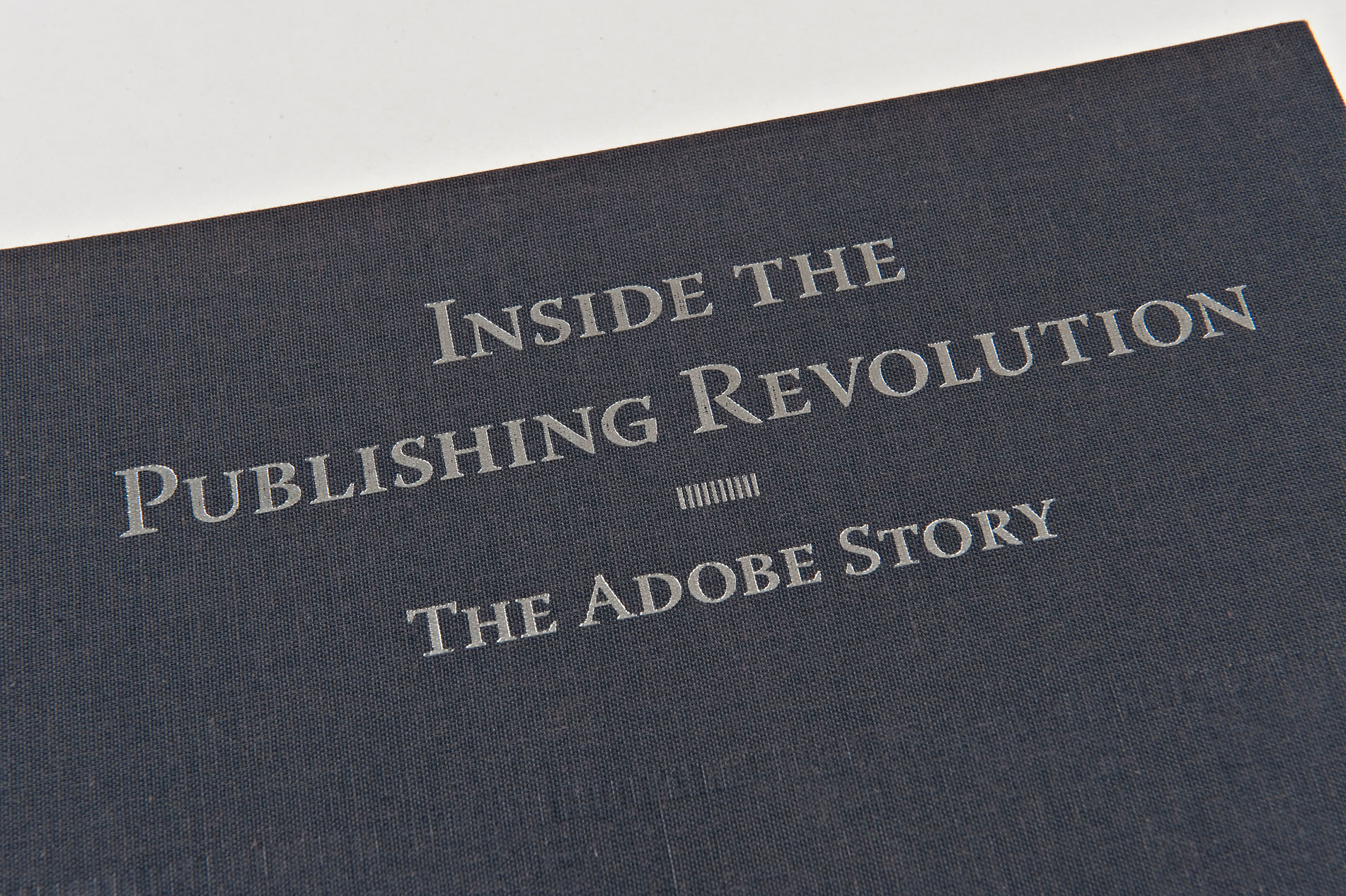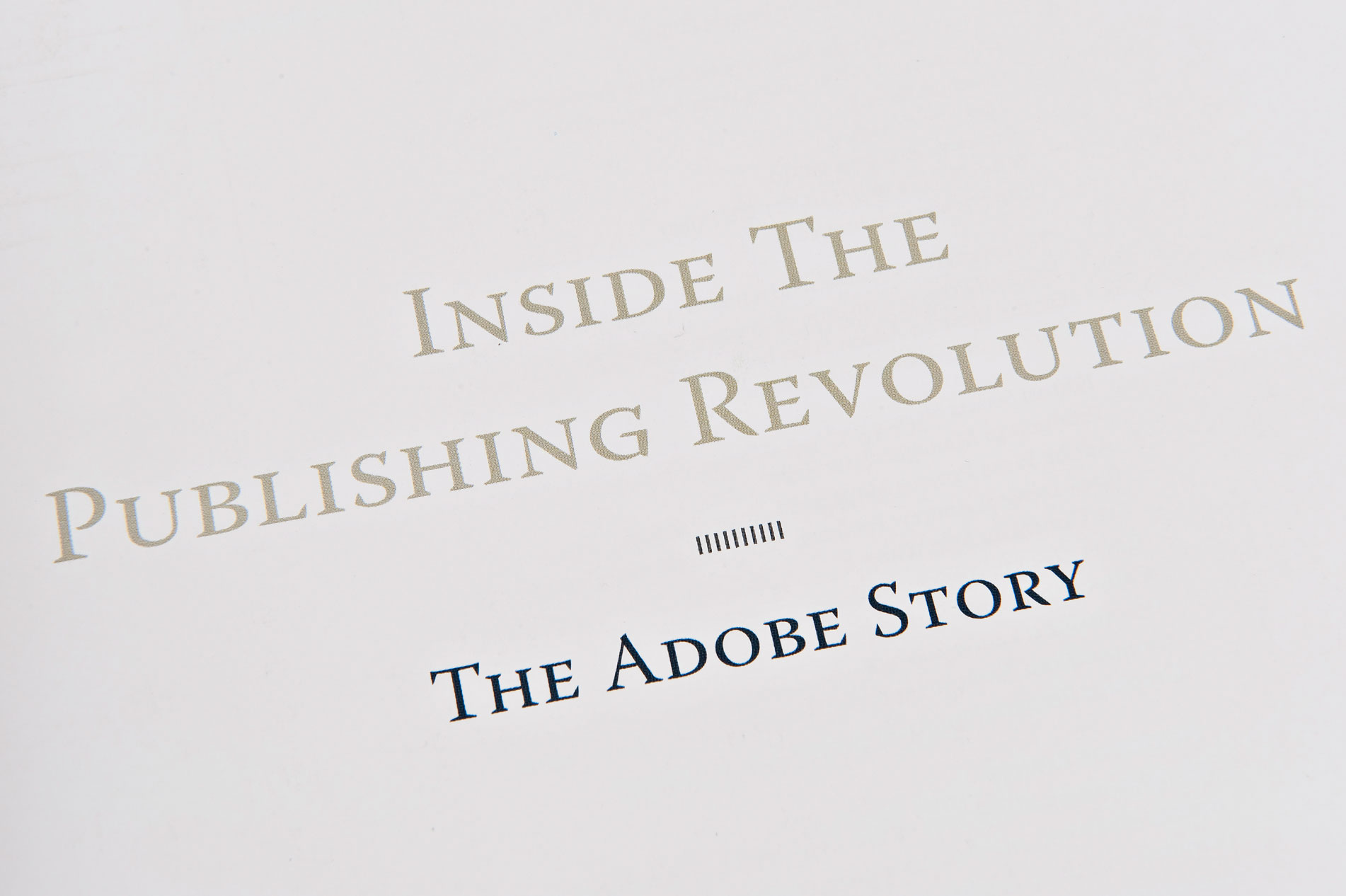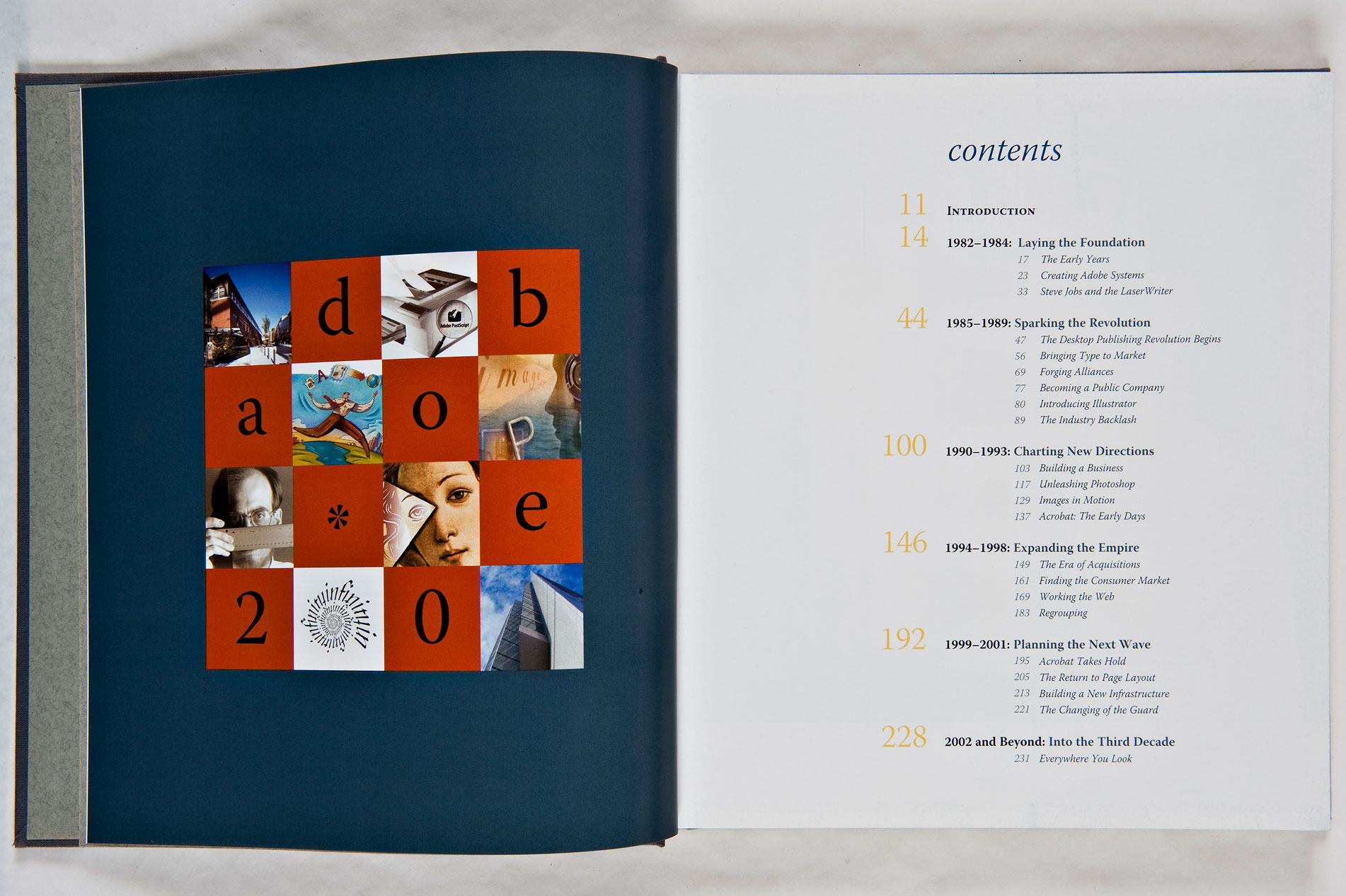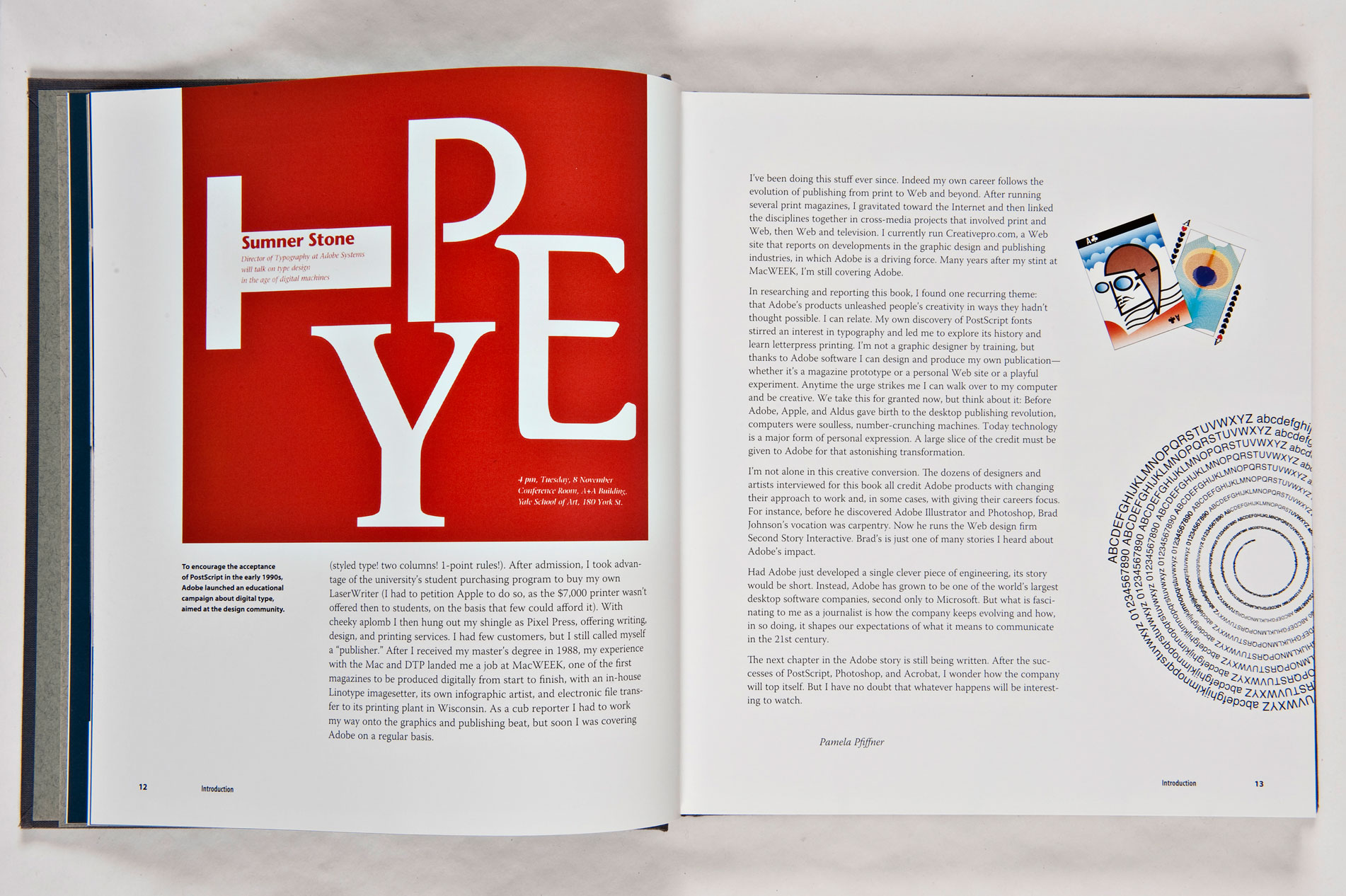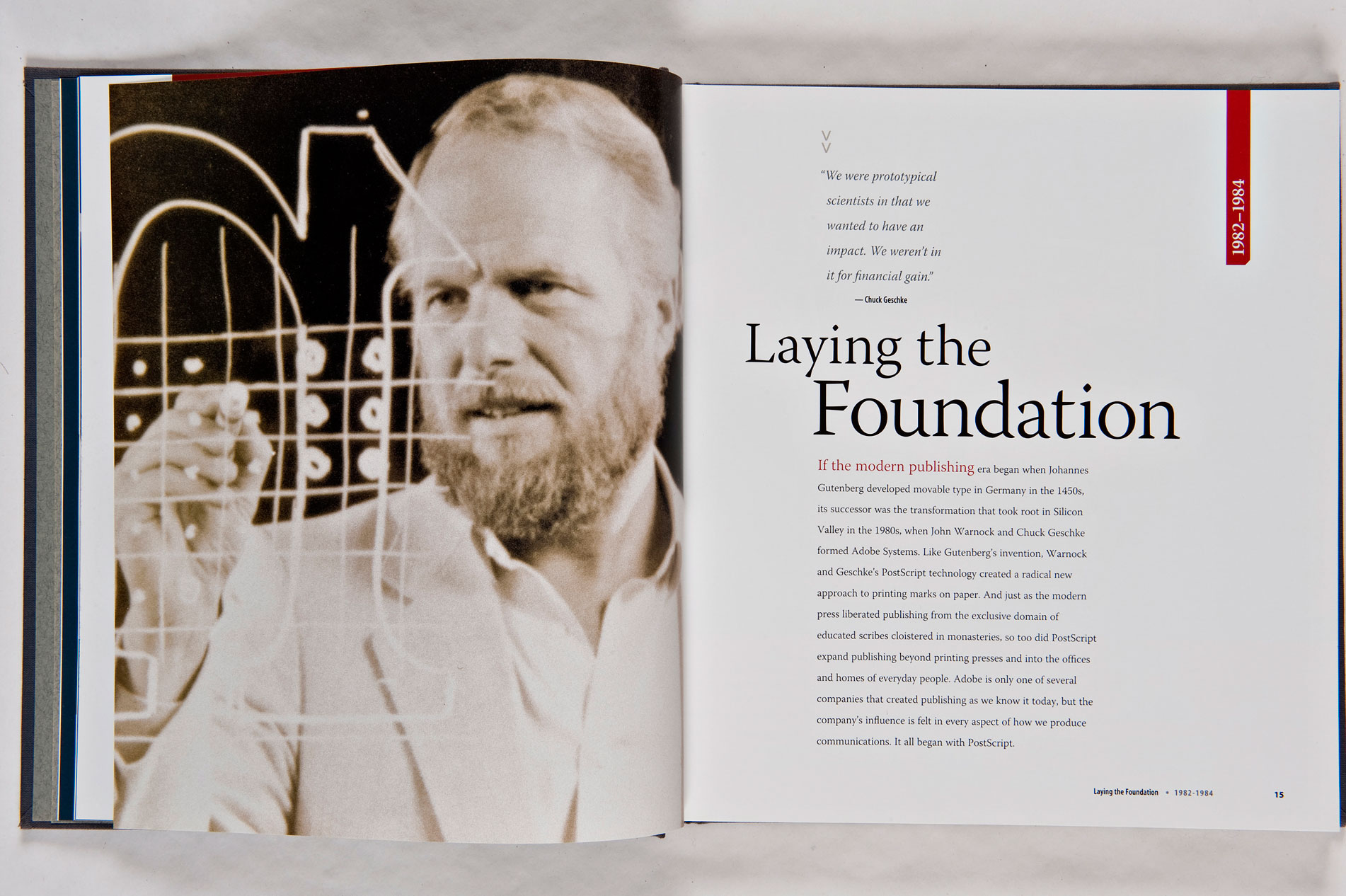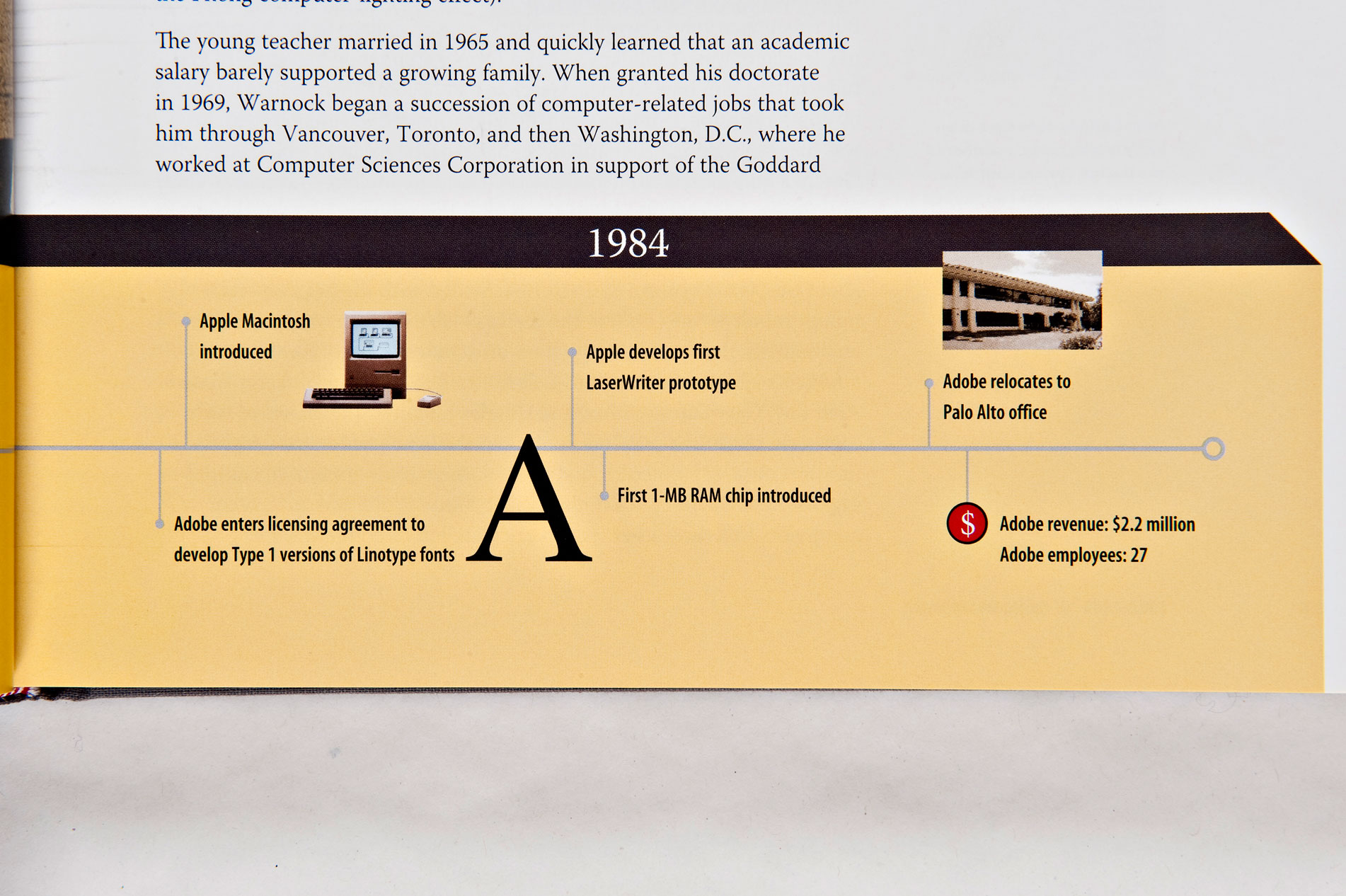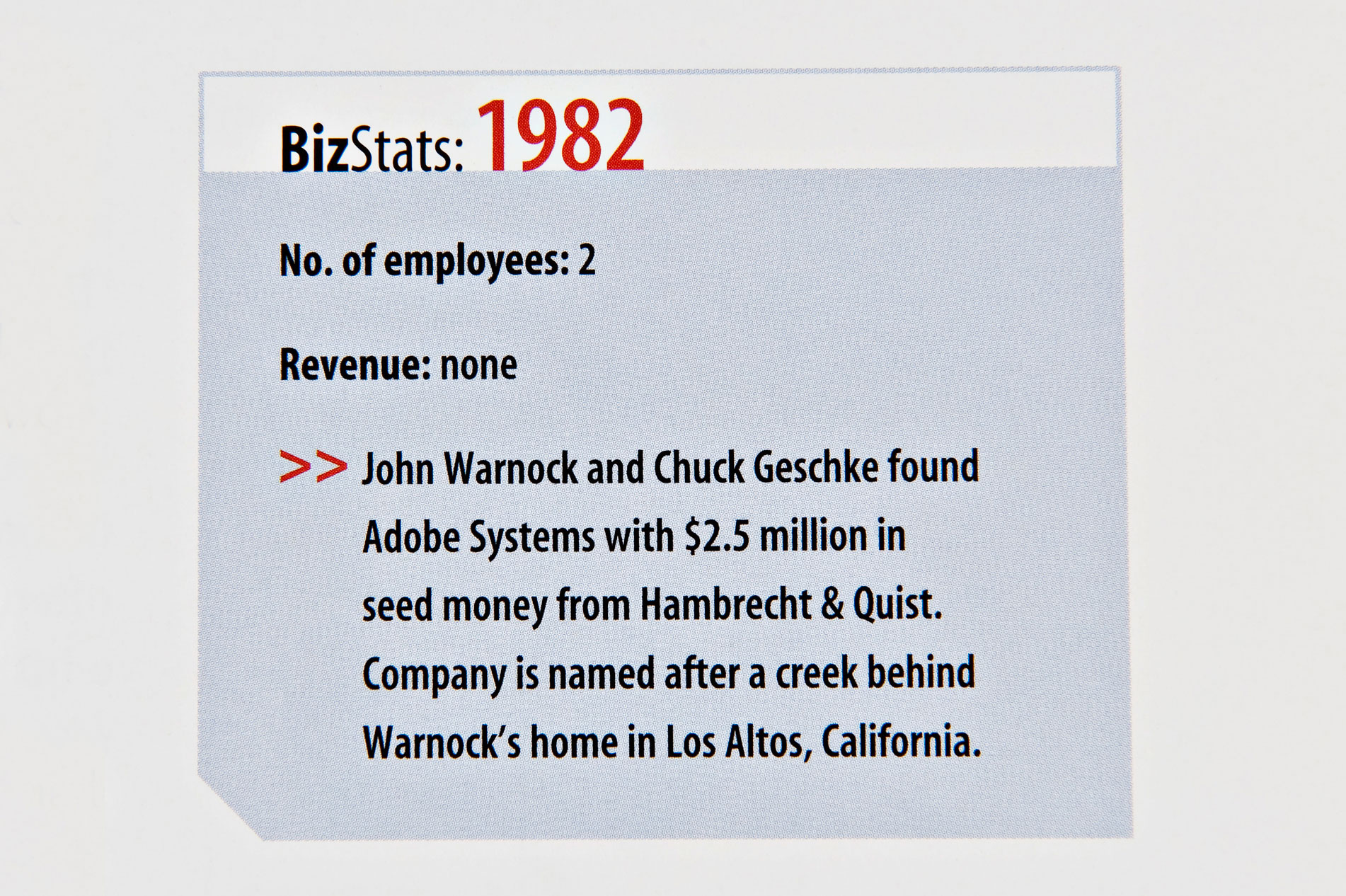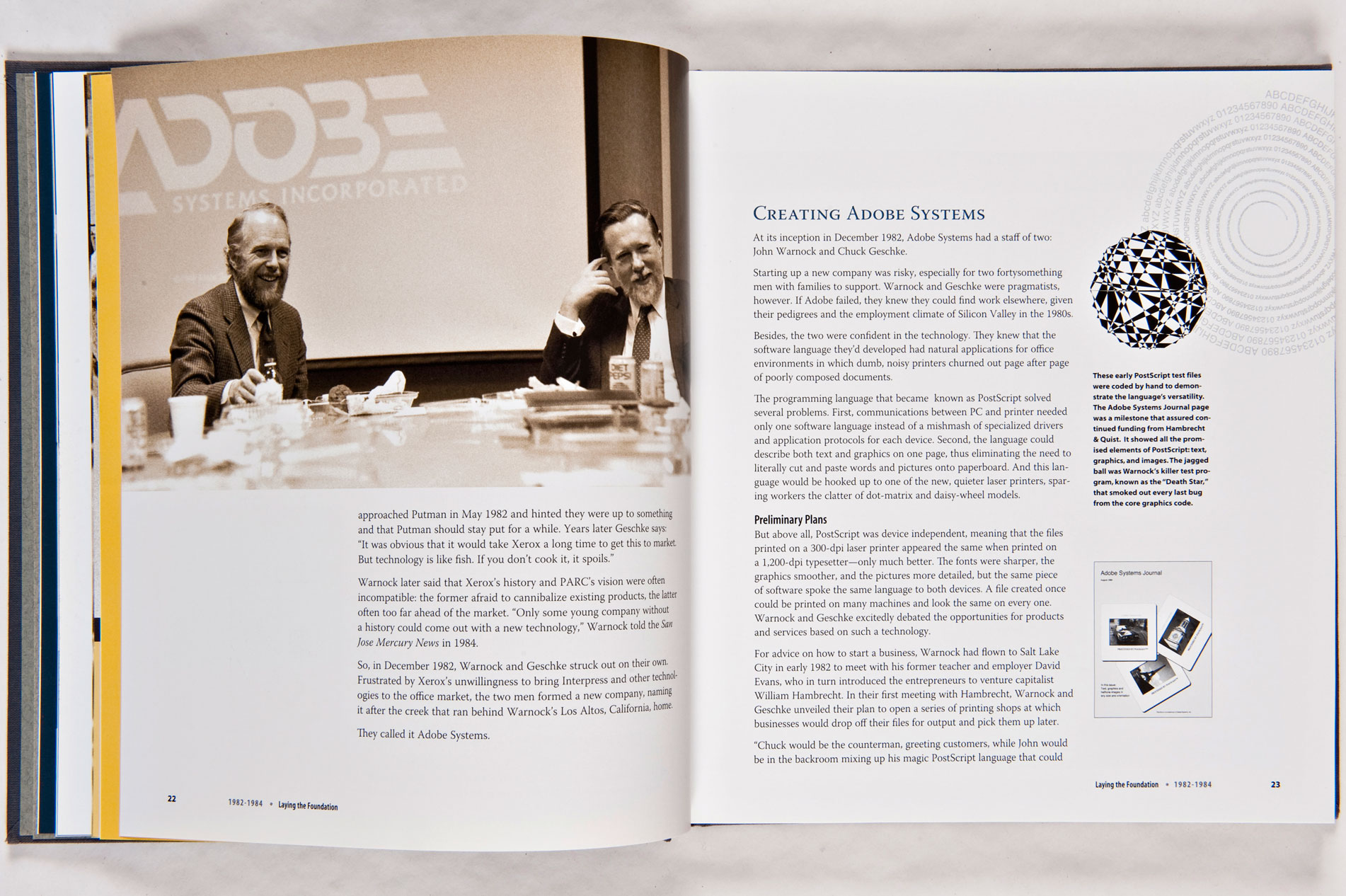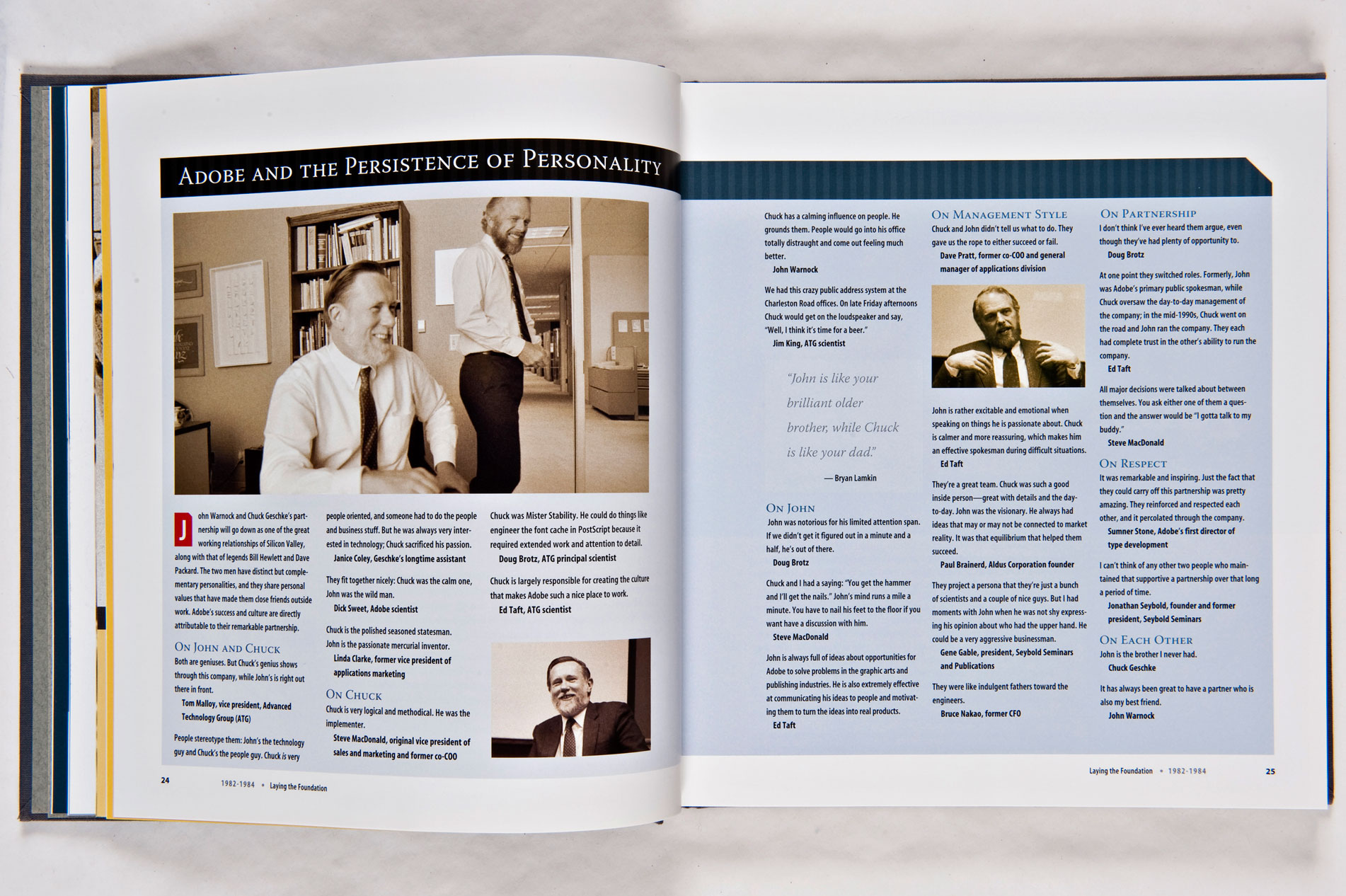
2001-2002 voit la naissance d’e-artsup, l’école supérieure de la création numérique. C’est très exactement 20 ans après la naissance de la société Adobe et des technologies qui allaient bouleverser le monde moderne. C’est pour mieux comprendre ces mutations, et les raisons qui ont fondé la création de notre école, que j’ai publié ce billet.
Ceci est la vidéo d’un simple livre. Mais, but what a book! celui qui reconsidère toute l’histoire vécue de l’aventure de la naissance du monde numérique tel qu’on le connait aujourd’hui. Le monde de digital est passé en vectoriel, les courbes de Bézier ont servi de tremplin pour le langage Postscript inventé par l’équipe de John Warnock. Puis ils connectent une Laserwriter postscript à un Macintosh (Steve Jobs 1985), puis, ils inventent les polices de Type I tout en faisant cadeau à l’humanité des brevets sur le Postscript (1989). Puis ils lancent dans la foulée Adobe Type Manager (ATM) qui permet enfin un vrai WYSIWYG à l’écran etc. 20 ans d’innovations qui ont bouleversé le monde à jamais. Et donc 1989-2009 nous fêtons cette année le vingtième anniversaire de cette naissance Grand Public, avec l’arrivée d’ATM.
Ne reste plus qu’à vous poser une question: si vous aviez l’âge de vivre ces mutations majeures et que vous travailliez à l’époque dans une agence de communication ou dans un bureau de créa, ou encore dans un studio de graphiste, comment avez-vous perçu ces évolutions? comment les avez-vous vécues dans votre quotidien?
Ce magnifique ouvrage à la gloire de l’histoire du langage Postscript et des innovations qu’Adobe a initié depuis plus de 20 ans est encore disponible sur le site d’Amazone, il s’agit pour le coup sans doute d’une édition quasi épuisé et j’espère qu’un jour il sera réédité tant il contribue à mieux nous faire comprendre les processus scientifiques, techniques, marketing et sociales qui ont changé notre monde d’avant en un monde de création à la portée du grand public. Inside the Publishing Revolution: The Adobe Story